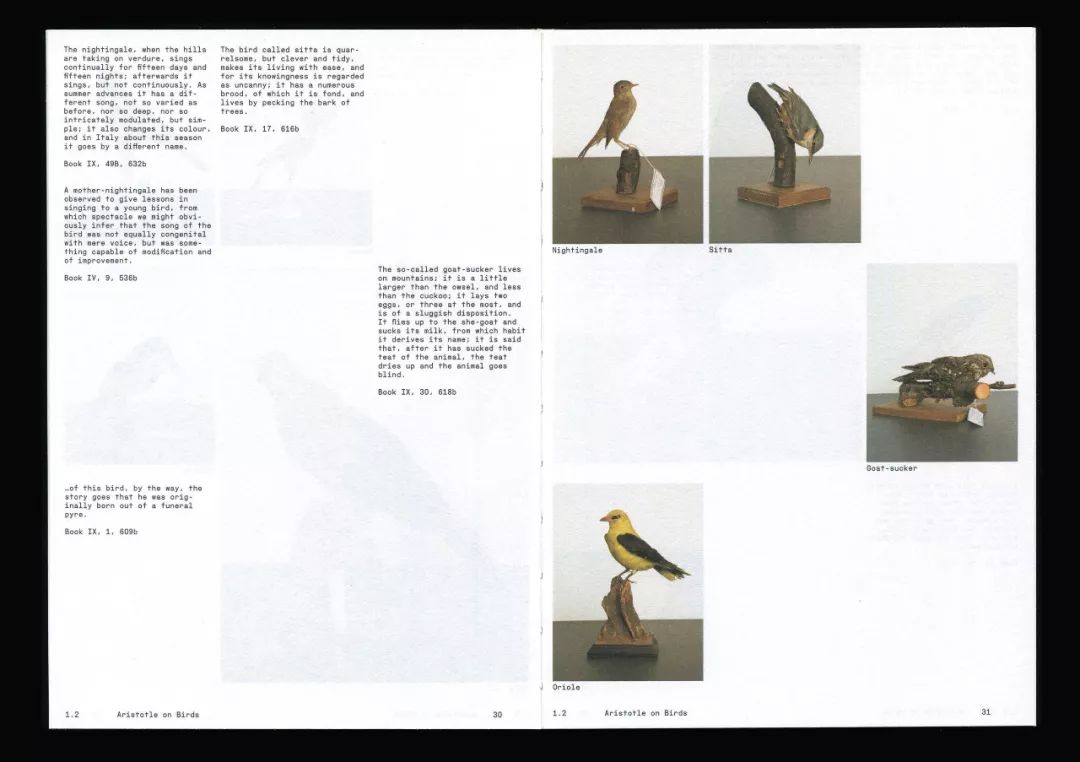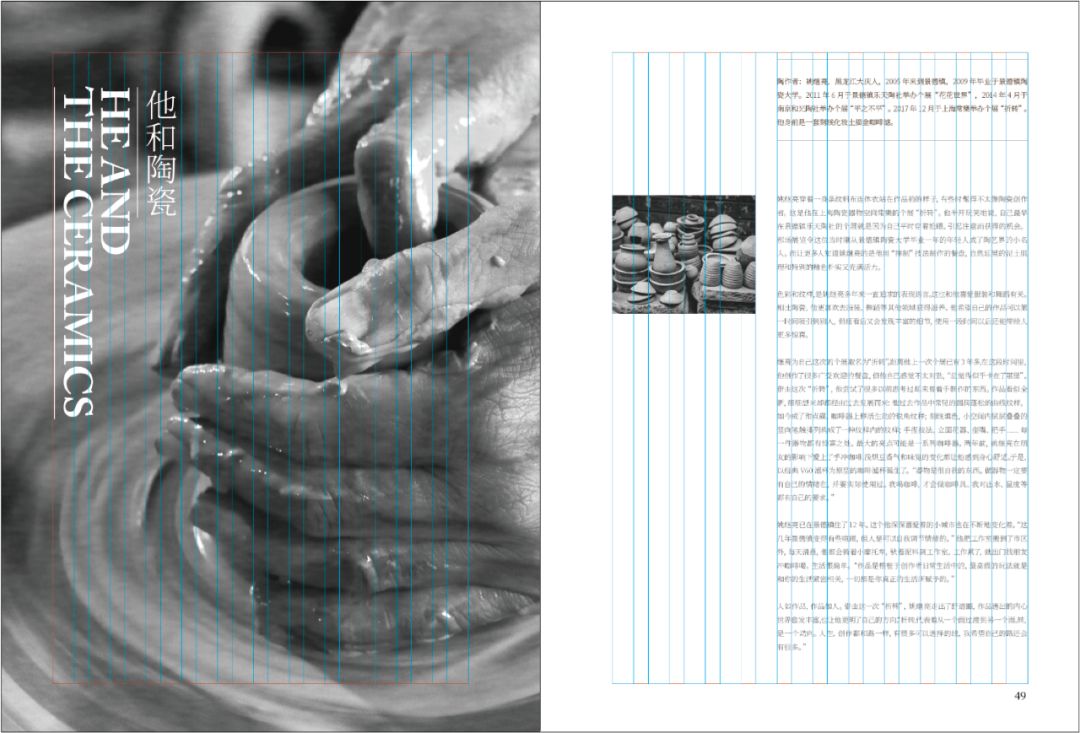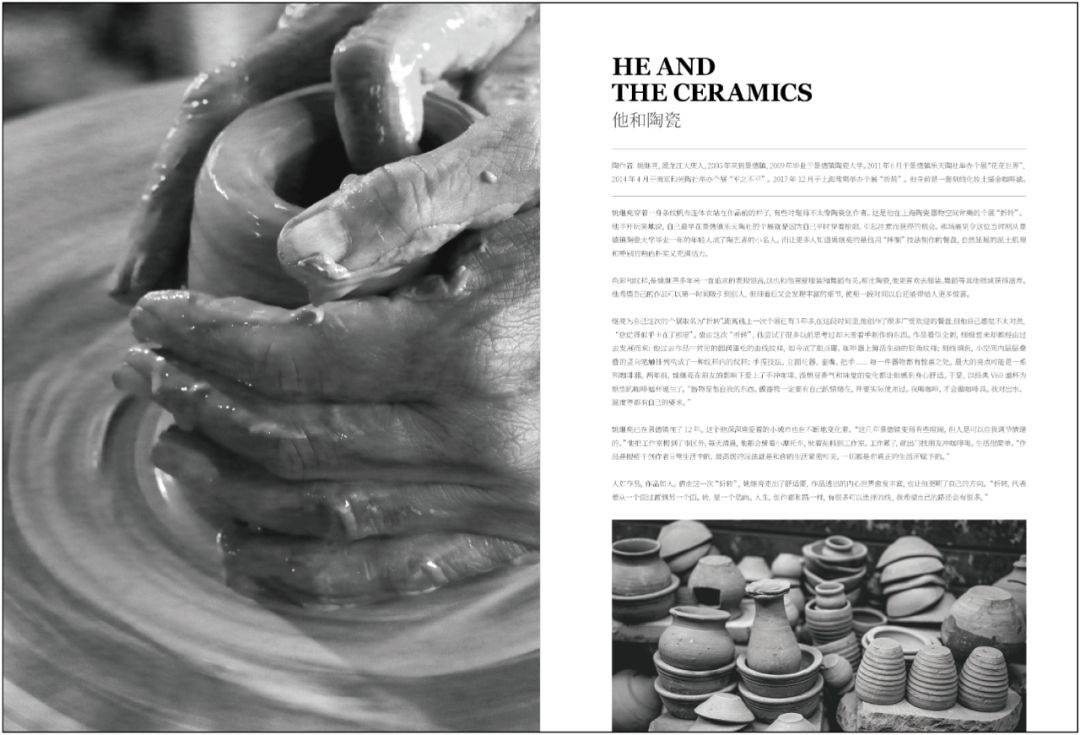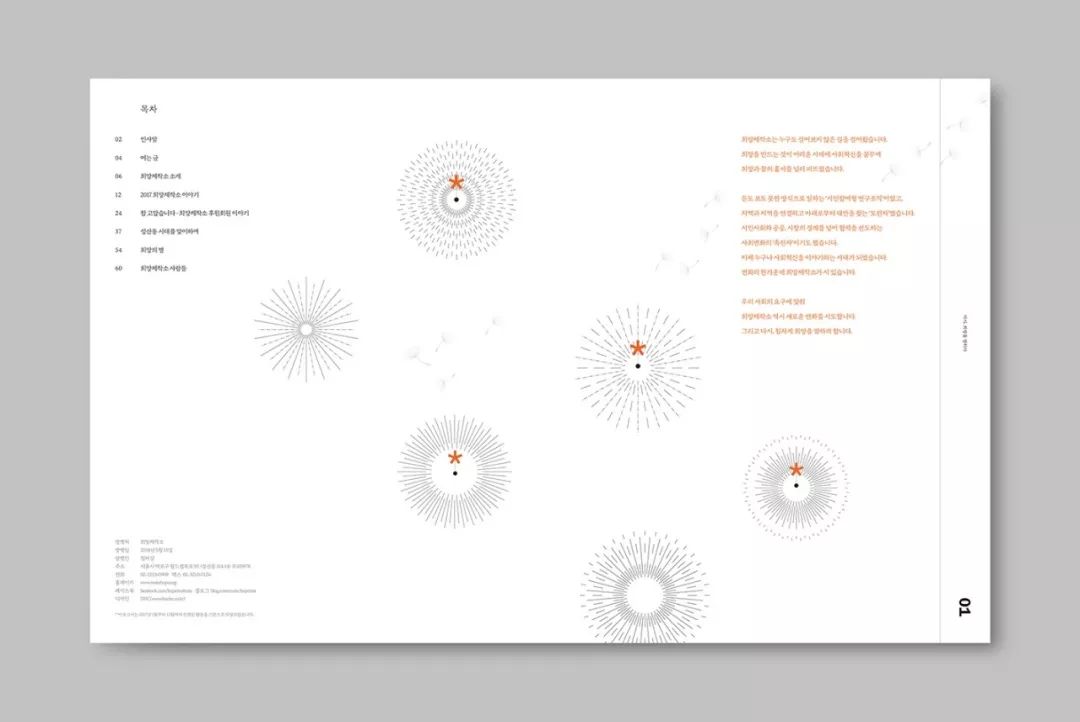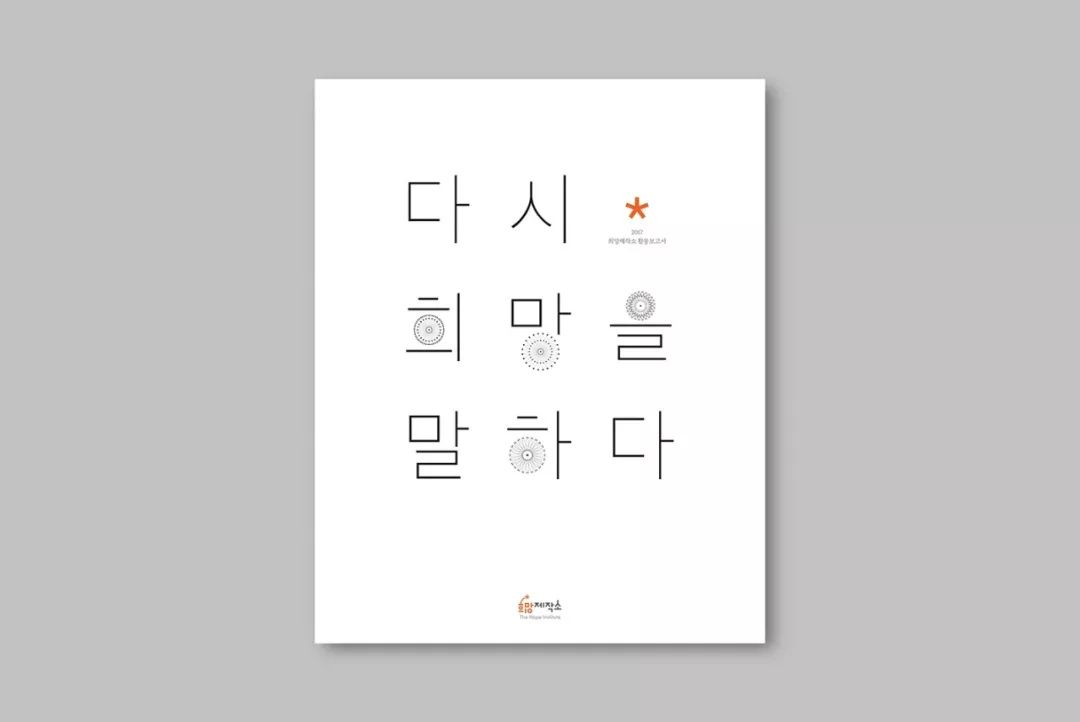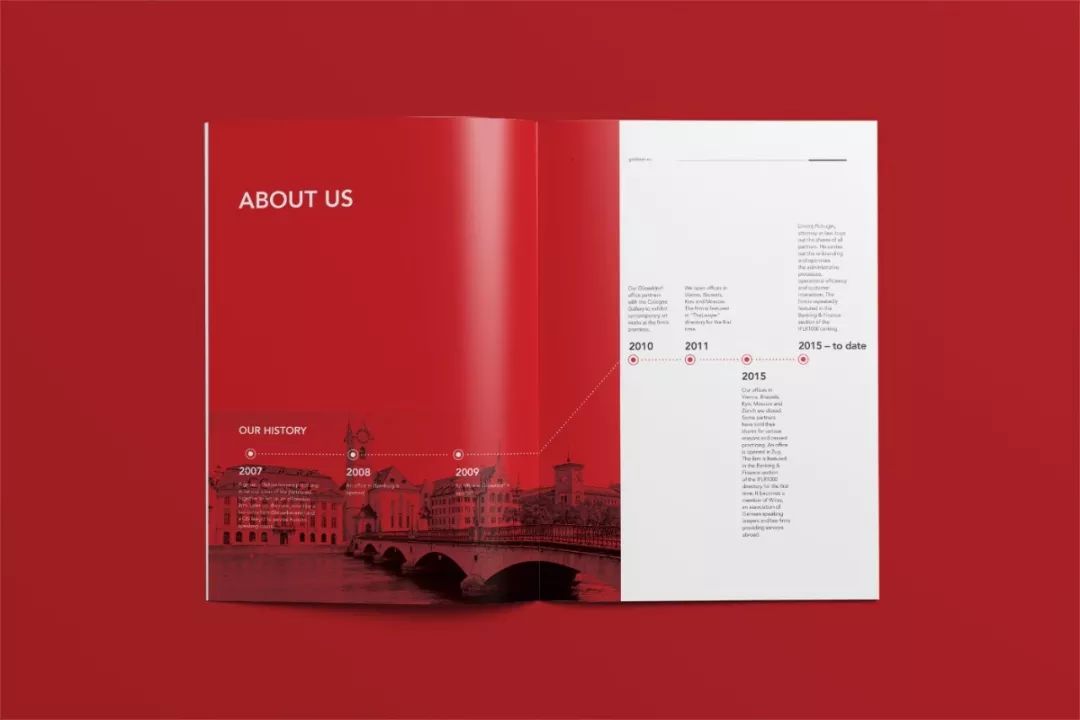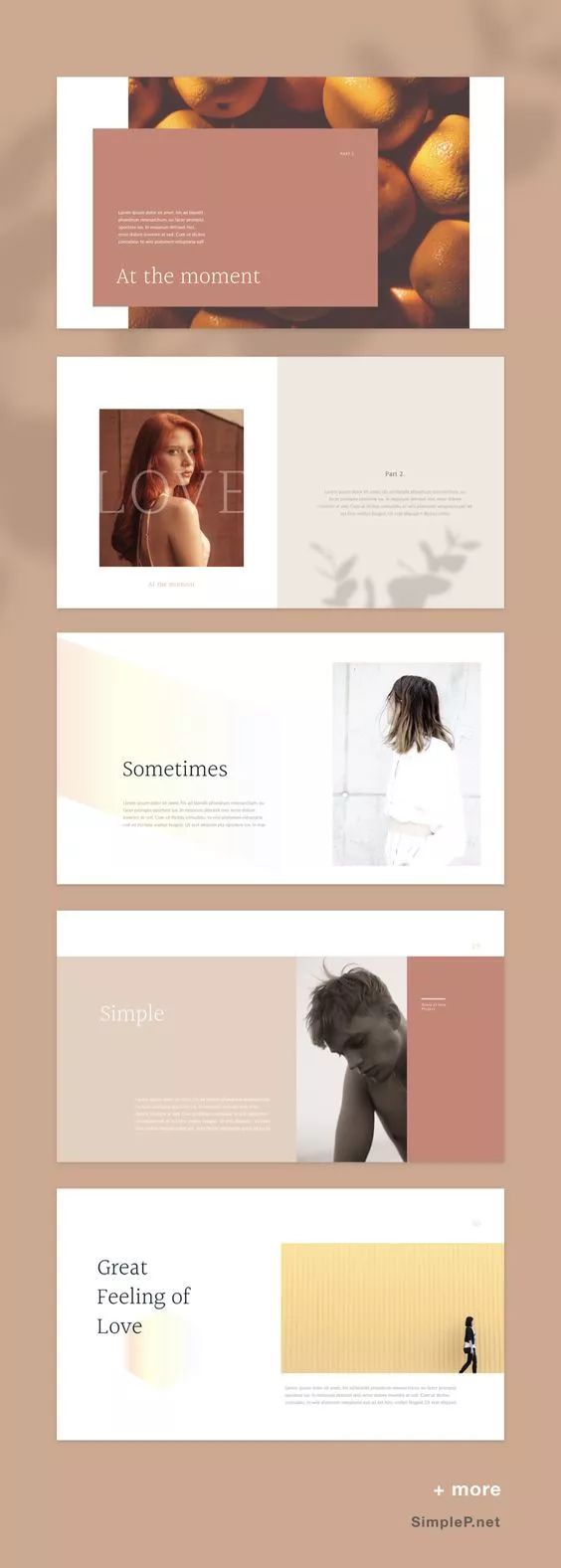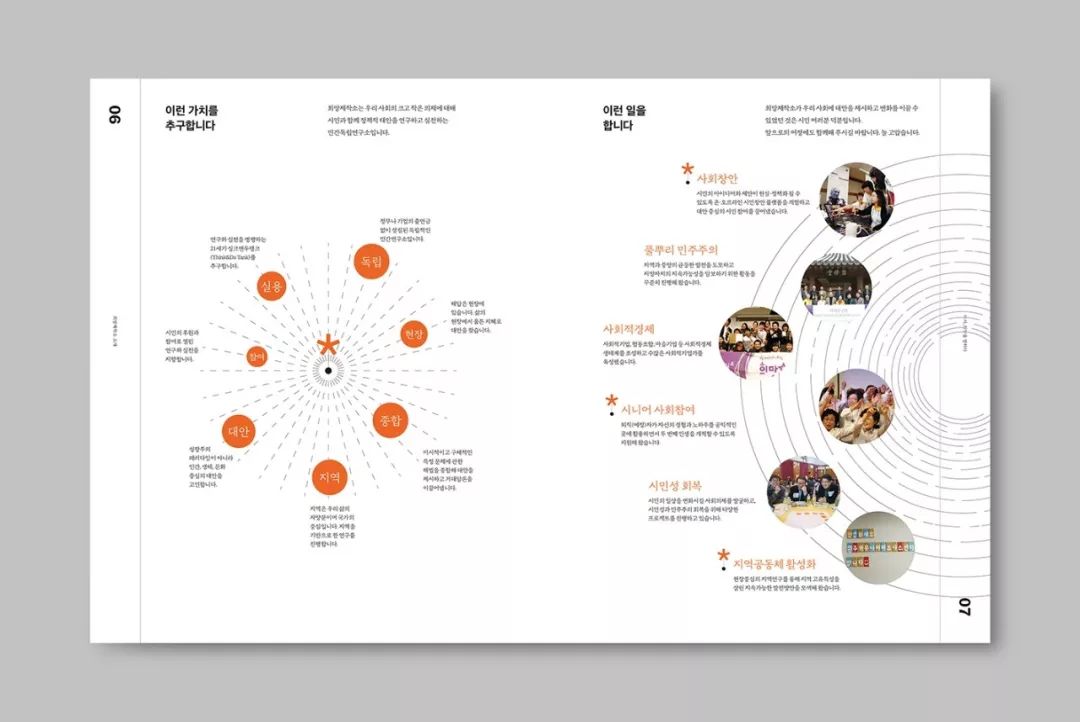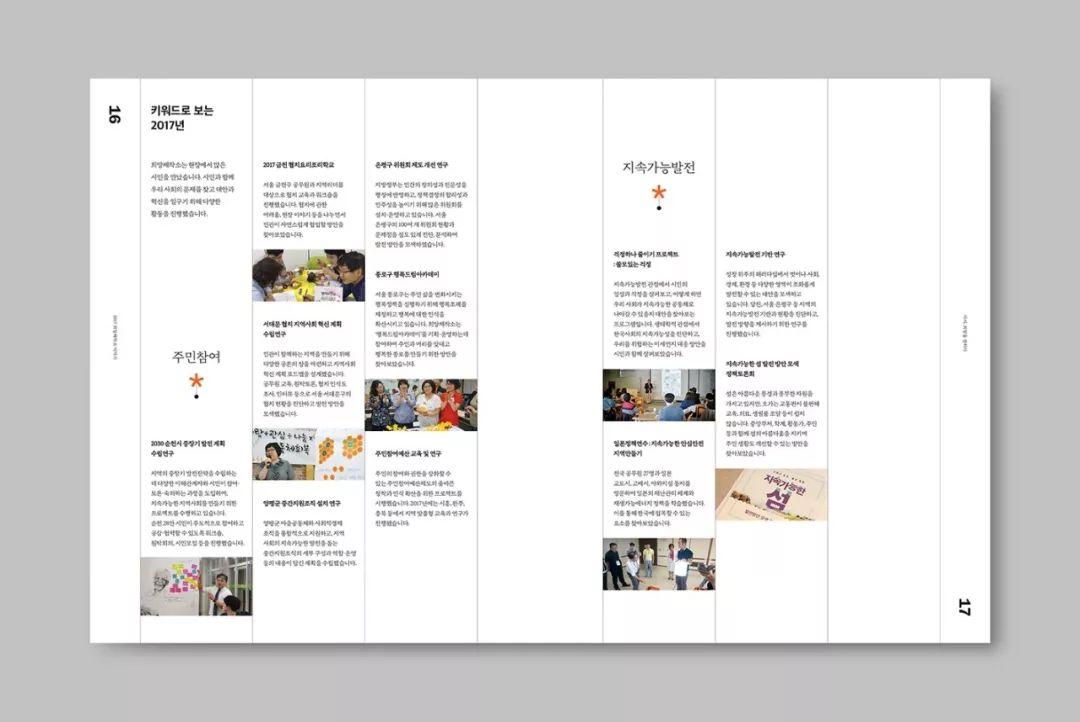
如何运用简约进行排版?这8个原则你必须要知道
很多时候我们接到项目,被告知客户要求做“简洁大气”的风格,那么怎样才能满足客户提出的需求,把简约的原则运用到排版中,下面为大家总结几点实用的原则:
善用对比
Use Contrast
按照简约设计的特征来看,良好的对比度对于整个视觉设计来说是特别明显的。在一个简约设计中,对元素对比的把握可以帮你决定读者的视觉阅读路线。而对比主要涉及到色彩对比,形状对比,以及位置等对比,这些都是关键性的对比变化。
▲ 数字大小对比
▲ 颜色对比
使用网格效应
Use Grid Effect
各位射鸡尸们也许都已经知道网格的用途,有些人甚至认为它对设计来说起着至关重要的作用。那么对于简约设计来说,就更是如此了。精密的网格系统能令文字、标题以及各个图形元素可以组成清爽、简洁并极富效用的设计。
▲ 只要稍微控制栏宽的宽度,并留出空白栏,就能营造出大页面的感觉。这种方式既能缓解大篇幅文段的阅读疲劳,还能给版面带来透气和留白感。
妙用留白空间
White Space
留白属于一个负空间的存在,就如空气中的氧气。有时候看起来只是空白而已,但是它绝不仅于此。留白并没有一个固定的颜色或状态去框架它,而是以各种不同的形式存在 有时候是一段文字,有时候是一个角版图,有时候是一个字词……巧妙留白可令设计平衡,避免杂乱,让画面通透起来。而下面的版面设计充分使用留白,达到高大上的极简风格。
梳理清晰的层级关系
Information Hierarchy
一个简约的画面可以令视觉的信息层级通畅无阻,所需信息一览无余。清晰的信息层级都令页面简单易读,发挥了强大的功能性。而清晰的信息层级一般是谁重要谁突出,因而有主次之分。将其优先级分辨罗列清楚之后,根据优先级进行设计(可通过色彩,大小,字形,位置等表现手法)。
▼ 以下版面设计中通过字体的大小和颜色的对比,和添加线框来区分信息间的层级。
尝试打破常规编排
Break Precedent
虽然简约风的编排表面上看起来是规整无变化,但是你可以突破常规思维,改变元素的位置和构图,让画面看起来带点设计感。如下面的版面使用了错位式的编排方式,完全打破了对齐性的排版,呈现出独特的效果,十分引人注目。同时,也保证了文字的可读性。
不只有单色或黑白
Other Colors
很多人认为简约设计只能使用单色或者黑白才能体现出简约,但事实并非如此。在用色上,我们可以既抓人眼球又保持简约,只要尽可能保持用色数量即可(1-3个颜色最佳)。下面版面使用了邻近色配色。
运用扁平式图形
Use Flat Graphics
扁平式的图形我们每天都能接触到,从手机app到电脑工具上。它们不仅极具功能性,而且能带来画面清晰感。在简约设计中也能起到有效的作用。图形有助理解,可以让阅读者更快速获取信息,并从视觉上引导用户理解你的设计。
选择高质量图片
Good Picture
站在设计的角度,一切事物要遵循一定的美感,而简约设计也是如此。所以说图片不能随意拿来使用,对图片本身的质量还是有所要求的,或者说最起码有个基本的要求,比如说清晰度不好的图片或者说太过杂乱的场景都不太适合。
虽然简约设计的优势很多,但它并非是万能。换句话来说,它的适用主题其实是有限制的,也并不是任何主题都能使用。可是有一件事是肯定的,画面越简约,设计目标和针对性就越明显,传达信息也就越有效。